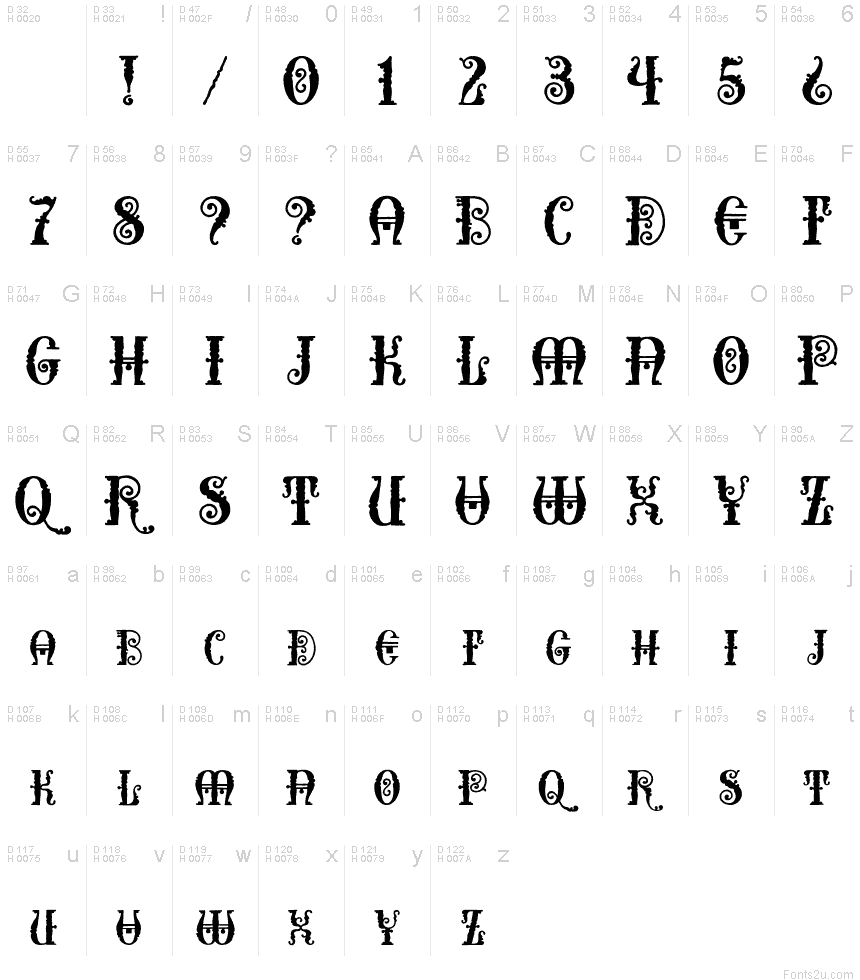
Krój pisma Erotokritos autorstwa Waltera Veleza to darmowy, dekoracyjny font w stylu retro, który wygląda, jakby został wyjęty ze starego plakatu cyrkowego lub wyblakłego afisza teatralnego. Grube, nasycone atramentem linie zderzają się z kręconymi zawijasami i dziwnymi wypustkami, nadając każdej literze nieco figlarny, ręcznie wycinany charakter – jednocześnie teatralny i tajemniczy. Krój jest na tyle wyrazisty, że świetnie sprawdza się samodzielnie w pojedynczych słowach, gdzie wszystkie zdobienia mogą w pełni wybrzmieć.
Dzięki Erotokritos błyskawicznie dodasz dramatyzmu plakatom koncertowym, okładkom książek, projektom w stylu vintage, menu barowym, grafikom na Halloween czy opakowaniom produktów butikowych. Zwarty rytm i ciężka tekstura sprawiają, że ten darmowy font najlepiej prezentuje się w krótkich hasłach, a nie w długich blokach tekstu, zwłaszcza w dużym rozmiarze. Zestaw go z czystym, minimalistycznym bezszeryfowym krojem w tekście głównym, aby jego ozdobny charakter pozostał czytelny i efektowny.